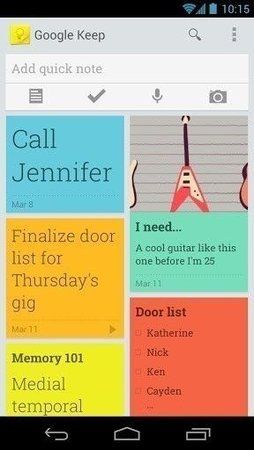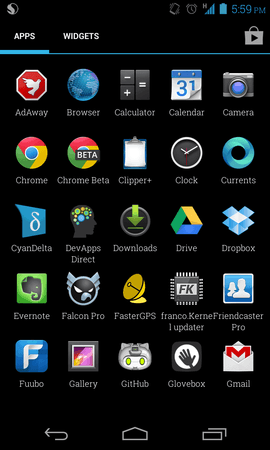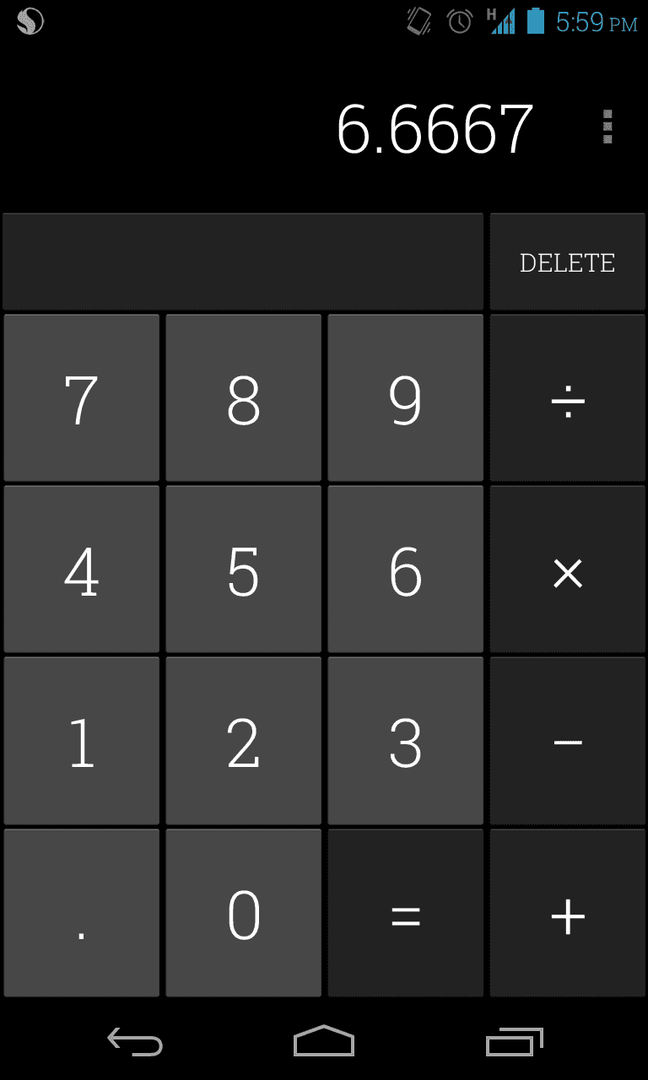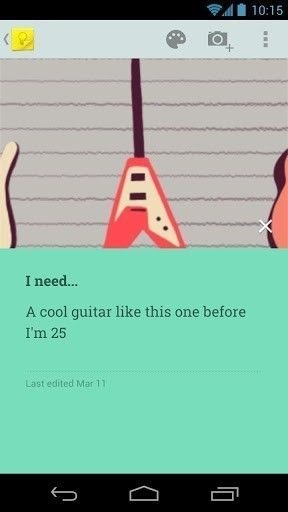
Ein interessantes Gerücht: Kommt in der nächsten Android-Version (Android 4.3 oder 5.0) ein neuer Schrifttyp zum Einsatz? Die bisher bekannte Variante der Schriftart Roboto könnte durch Roboto Slab ersetzt werden, wenn man den Bildern rund um den Launch von Google Keep glauben möchte. Ein findiger Designer hatte nämlich sofort gemerkt, dass die Schrift sich von der üblichen Android-Zeichendarstellung unterscheidet, wenn auch nur bedingt. Um zu veranschaulichen, wie Android unter Roboto Slab aussehen würde, setzte dieser clevere Typ es einfach als System-Standard und postete Bilder (siehe unten), die uns einen Vorgeschmack auf das liefern, was uns möglicherweise bald erwarten könnte. Woher der Hype um die neue Schrift? Tatsächlich ist Google Keep die aktuellste App, die es derzeit von direkt von Google gibt. Auch Bilder des neuen 4.0 Play Store, den unter anderem Androidpolice "gefunden" hat, sprechen für eine Verwendung von Roboto Slab in zukünftigen Android-Veröffentlichungen. Tatsächlich steht die Google I/O so gut wie vor der Tür. Einige Neuvorstellungen erwartet man dort allemal - also warum nicht auch eine neue Schrift? Ansprechend sehen die Screenshots jedenfalls allemal aus. Oder was meint ihr?!